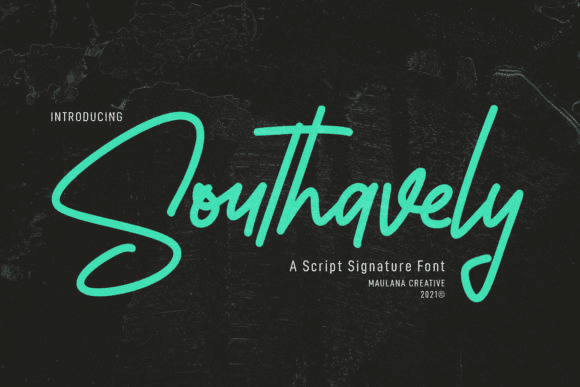
Название: Southavely Font (2021)
Southavely Script - это плавный и стильный шрифт.
Он прекрасно смотрится на различных дизайнах, требующих индивидуального стиля, таких как свадебные приглашения, благодарственные открытки, свадьбы, поздравительные открытки, логотипы и так далее.